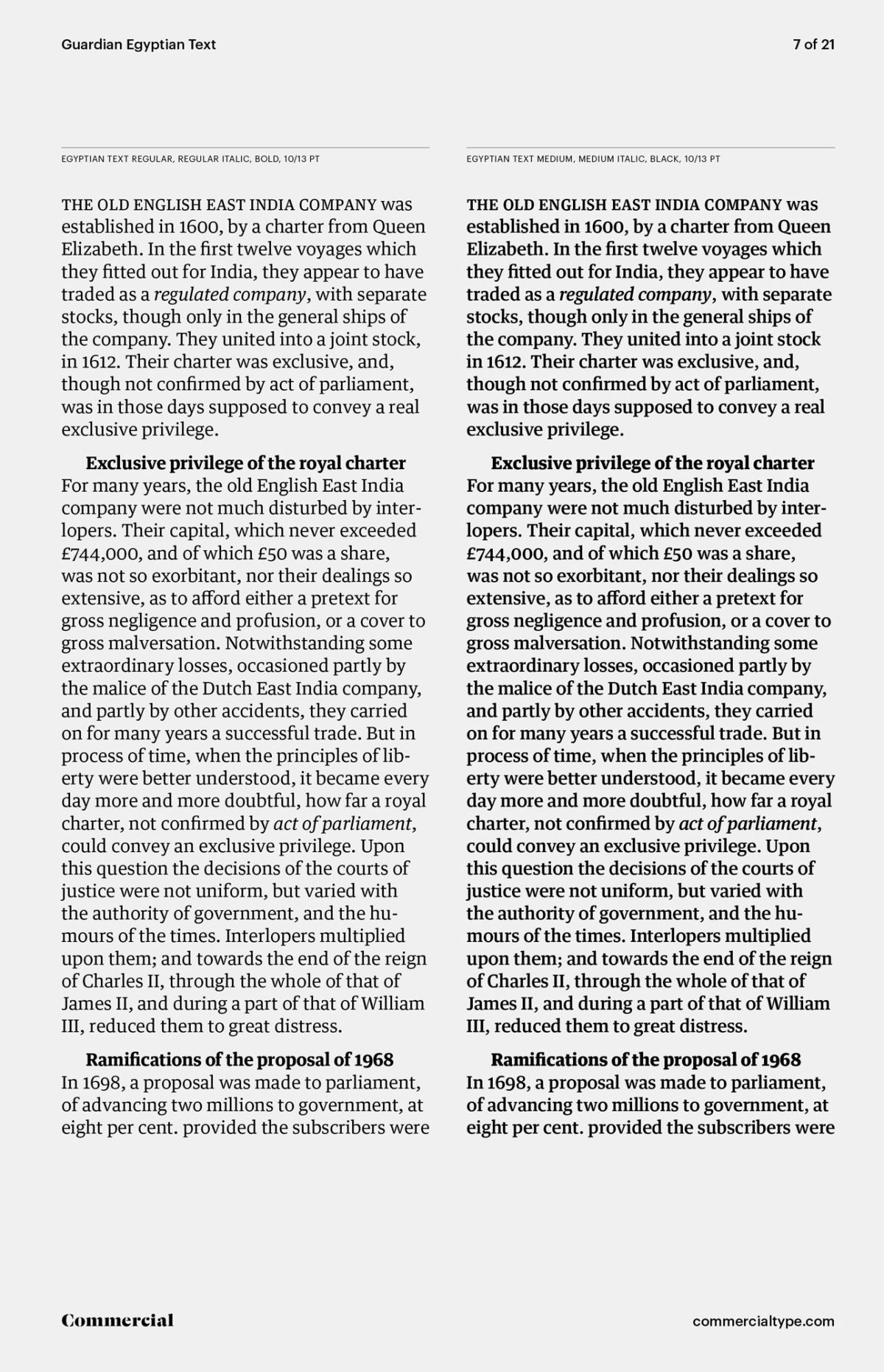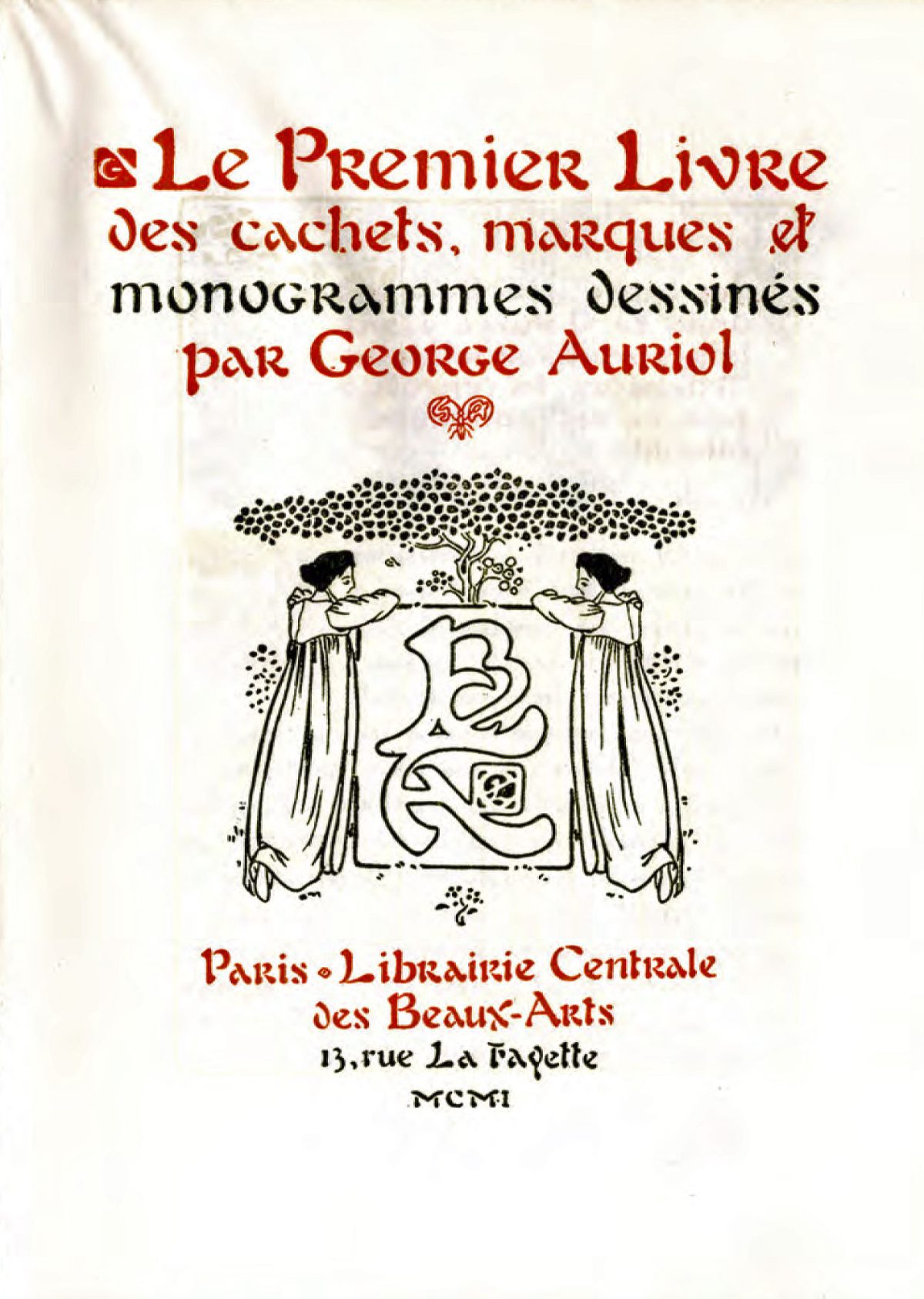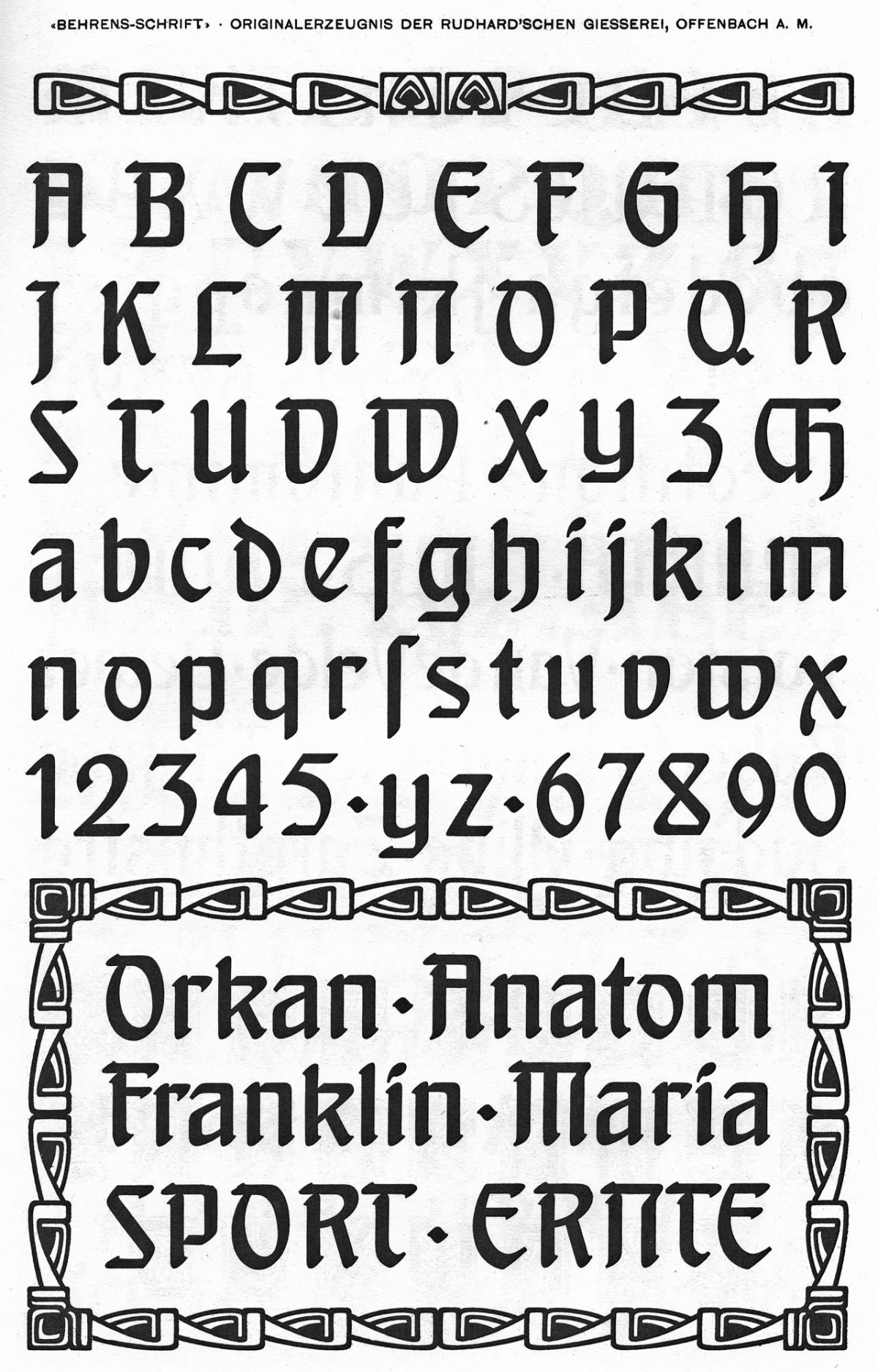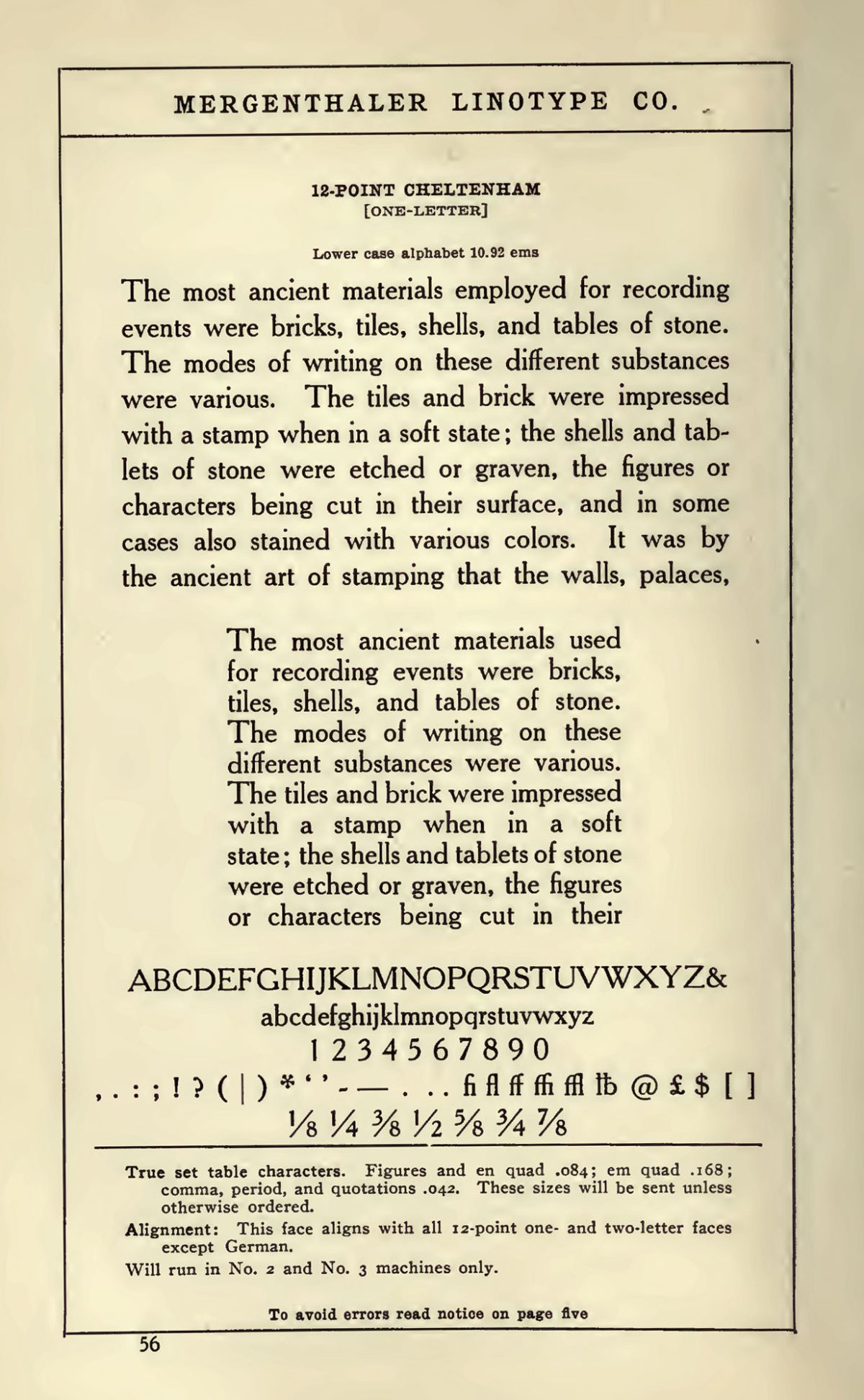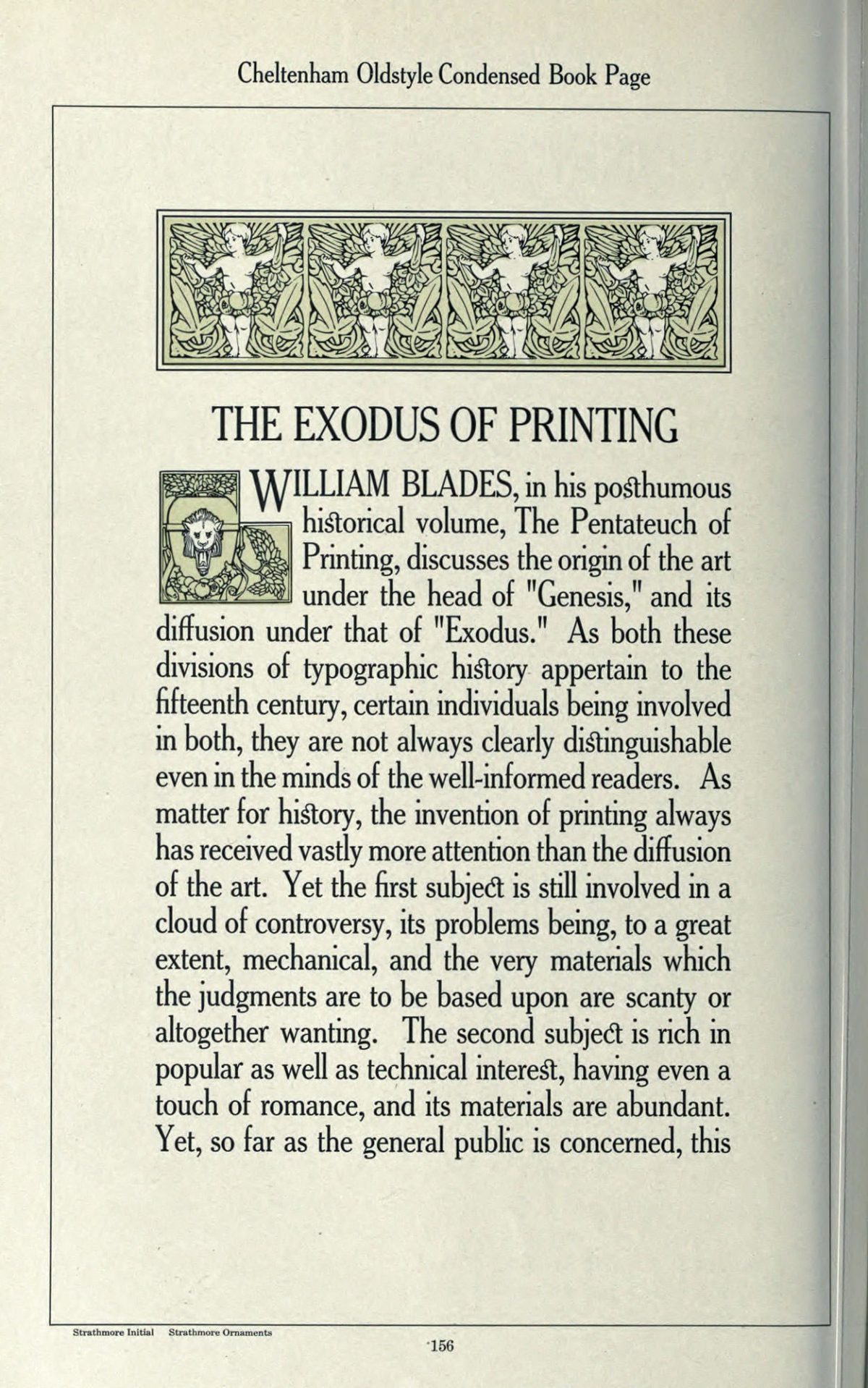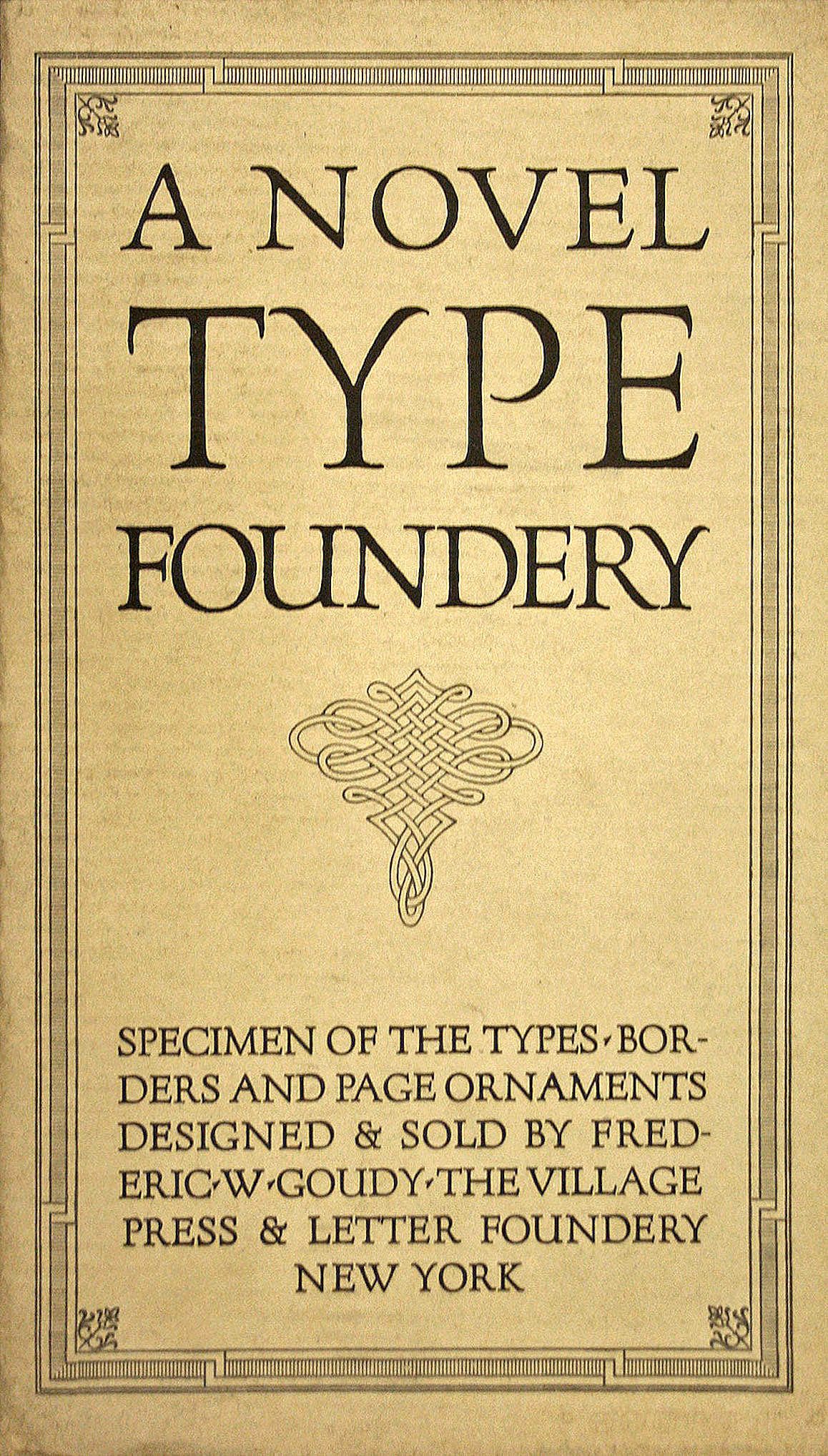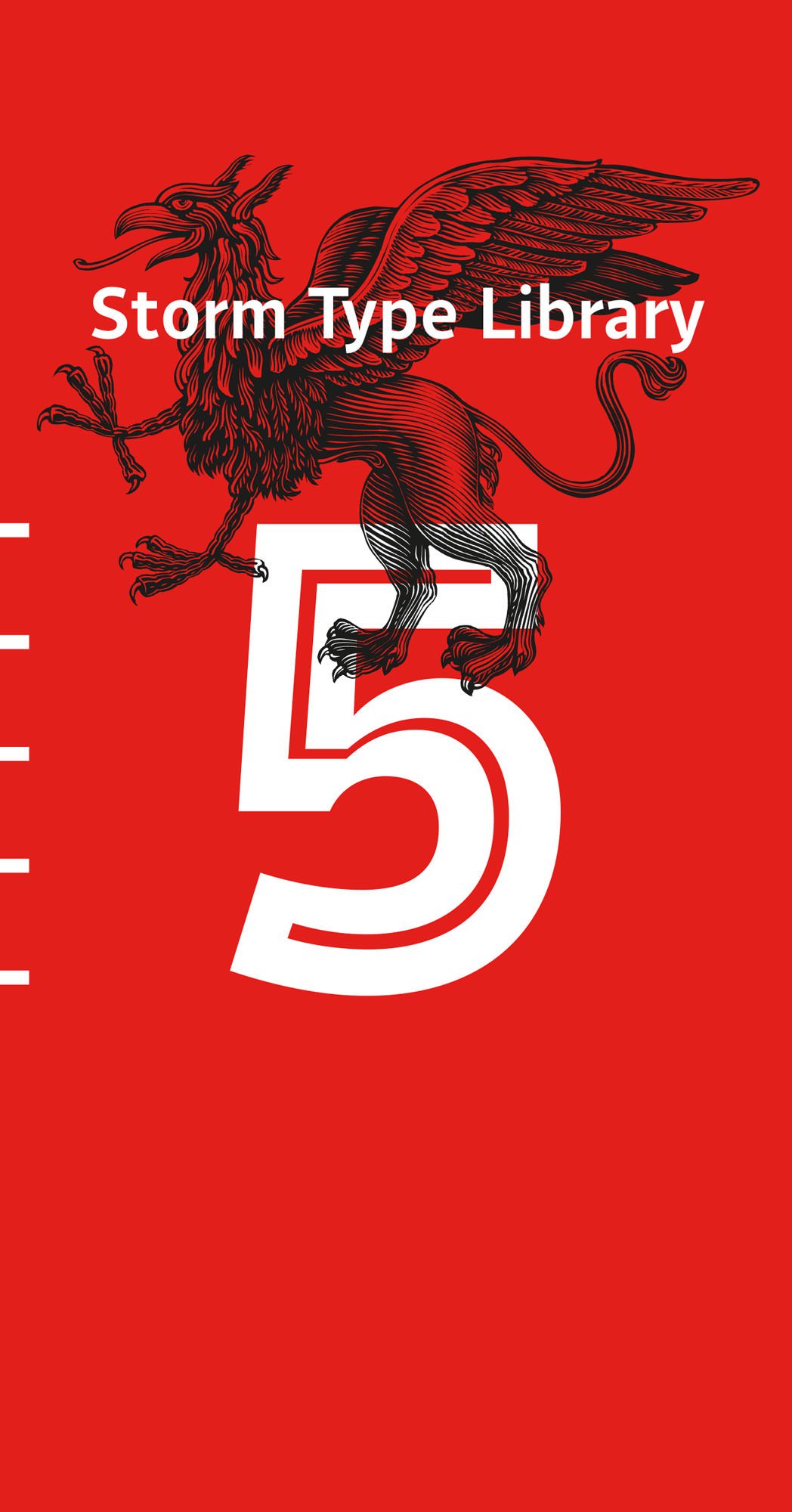
El espécimen tipográfico. ¿Herramienta de trabajo u objeto de placer? [Parte II]
El universo de la tipografía está lleno de sutilezas y detalles, de formas que transmiten ideologías a través de sus trazos. El espécimen tipográfico es el mundo que antecede a la puesta en página y donde sobran pretextos para observar el color de la trama, el contraste, el espacio entre las líneas y las letras; es el lugar donde se originan las combinaciones infinitas de los signos que esperan inertes y que aún no toman sentido en un discurso, pero que son para disfrutarse. Esta reflexión pretende esbozar el vasto mundo de una herramienta tan importante, poco recurrida y bastante desaprovechada en nuestros días. Para entenderla, es preciso conocer sus orígenes y el desarrollo que tuvo en las distintas épocas. (Esta es la segunda de tres entregas del texto.)
El catálogo ornamentado y la introducción del color
Gracias a la invención de la litografía, a finales del siglo XVIII, y al perfeccionamiento del grabado en metal, las fundiciones de tipos que se consolidaron en el siglo XIX como grandes industrias de impresión, impusieron una nueva estética en el diseño de catálogos, donde predominaron los paisajes, alegorías, marcos, bigotes y esquinas de calidad superior en comparación con lo existente en xilografía, y también emplearon color pero de manera modesta. Esta moda influyó sobre la tipografía dando rienda suelta al ornamento y a efectos visuales llamativos, mismos que enriquecieron los catálogos de las nóveles corporaciones de impresión como la New York Type Foundry 1 (1813, imagen 21) y la Boston Type (1818, imagen 22).
Imagen 21. Portada del catálogo de 1882 de la New York Type Foundry [1882]. Victorian frames, borders, and cuts from the 1882 type catalog of George Bruce's Son and Co. Nueva York: New York Public Library. Imagen tomada de: Etsy Studio. https://goo.gl/XGph2U
Imagen 22. Espécimen de combinación del catálogo de tipos de la Boston Type [1892]. Type Specimen of the Boston Type Foundry. Boston: The California Historical Society, 1892. Imagen: Jaime Henderson. https://goo.gl/CjvjbB
Además de lo anterior, la tendencia se tradujo en tipos con cuerpos de grandes dimensiones 2 y de aspecto mecánico, con patines gruesos y cuadrados, denominadas «egipcias», como se aprecia en el trabajo del inglés Vincent Figgins (imagen 23) —quien introdujo ese estilo en el Reino Unido—, el londinense Joseph Fry (imagen 24), con un tipo mucho más fino basado en la propuesta de Baskerville, o el del alemán Justus Erich Walbaum (imagen 25), similar al anterior pero con un cuerpo más robusto y de aspecto cuadrado, inspirado en los diseños de Didot y Bodoni. Más tarde se introdujeron letras muy ornamentadas como las toscanas que se desarrollaron durante la época victoriana y que, a propósito, Figgins, Fry y Thorowgood también hicieron propuestas.
Imagen 23. Espécimen de cuatro estilos dentro del catálogo de tipos de Vincent Figgins [ca. 1815]. Vincent Figgins Type Specimens - 1801 and 1815. Facsímil. Londres: Printing Historical Society, 1967. Imagen tomada de: “La Herencia Europea. Parte II”, A. Lo Celso. https://goo.gl/pBsXAH
Imagen 24. Espécimen de la Baskerville Old Face [Fry Baskerville] probablemente grabada por Isaac Moore en 1768. La gran demanda de tipos de Baskerville hizo que muchas fundidoras copiaron sus diseños. Specimen of Printing Types, by Fry and Steele, Letter Founders to the Prince of Wales. Londres: T. Rickaby. 1794. Imagen tomada de: “Joseph Fry”, Luc Devroye. https://goo.gl/3uoGjW
Imagen 25. Espécimen del tipo Walbaum romano e itálico [ca. 1803]. Este espécimen impreso por la Neon Type Division, en 1962, emplea las fuentes originales grabadas por Justus Erich Walbaum. La Typefounders de Chicago adquirió la Neon Type en 1959. Fuente: Archive.org [https://goo.gl/Pf4UNP]. Walbaum Specimen. Chicago: Typefounders of Chicago, Neon Type Division, 1976. Imagen: The Wallace Center, Cary Graphics Art Collection, Chicago, 1976.
Hasta este momento el uso de especímenes de fuentes se diluyó bajo la demanda de tipos de corte ornamental, aflorando el catálogo como el medio preferido para recorrer de un vistazo la variedad de tipos ofrecidos, además del llamativo empleo del color, que a su vez se enriqueció desde la introducción de la cromolitografía (1837). El efecto se vio reflejado principalmente sobre el cartel 3 con la sobrecarga de color y una fuerte influencia neoclásica (imagen 26). Como consecuencia, estas manifestaciones dieron origen a las artes decorativas, de donde surgieron diseñadores de tipos como Georges Auriol (imagen 27), Peter Behrens (imagen 28) y Will Breadley (imagen 29), cuyas propuestas, a pesar de su limitada producción, fueron muy representativas al igual que los especímenes que publicaron.
Imagen 26. Espécimen de fuentes y viñetas de Charles Derriey [1839]. Épreuves des Caractères & Vignettes. Paris: Charles Derriey, 1839. Colección privada de Jan Tolenaar. Digitalización: Taschen. Imagen tomada de: Type. A Visual History of Typefaces and Graphic Styles, volumen I: 1628-1900. P. 130.
Imagen 27. Espécimen de fuentes, marcos y ornamentos de Georges Auriol [1901]. Le prémier livre des cachets, marques et monogrammes dessinés par George Auriol. Paris: Librairie Centrale des Beaux-Arts, 1901. Digitalización: Archives de Lure. https://goo.gl/tGjj8C
Imagen 28.
Espécimen de la Rudhardsche Behrens Schrift [ca. 1901]. Behrens Schriften. Initialen und Schmuck nach Zeichnungen von Professor Behrens, Offenbach: Rudhard’sche Giesserei, 1902. Imagen tomada de: “Peter Behrens”, Luc Devroye. https://goo.gl/fWW4HY
Imagen 29. Publicidad para The Ault & Wiborg Company [1985]. Will H. Bradley: An American Artist in Print. Vermont: Hudson Hills Press LLC., 2002. Imagen tomada de: “Pioneer of American Art Nouveau: William H. Bradley”, The Wolfsonian-FIU. https://goo.gl/JjEgzc